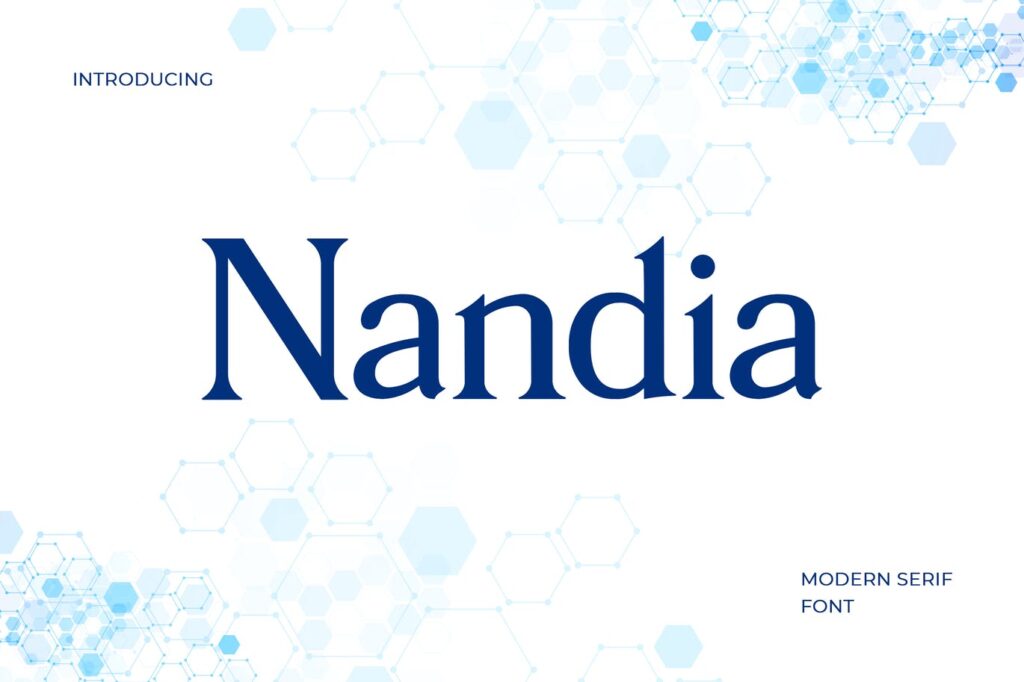
Nandia Font
Nandia es una moderna fuente Con serif inspirada en tipografías transitorias y contemporáneas. Mondia ha sido diseñado con una relación de caracteres de alto contraste para dar un toque elegante, y alta altura x para dar más legibilidad a las frases.
Nandia ofrece muchas posibilidades para ser aplicado en muchos proyectos gráficos o editoriales. Fabricación de texto de cita, logotipo, revista de cabecera, diseño de camiseta, diseño de concepto hechos a mano, etc.
Nandia Serif Typeface